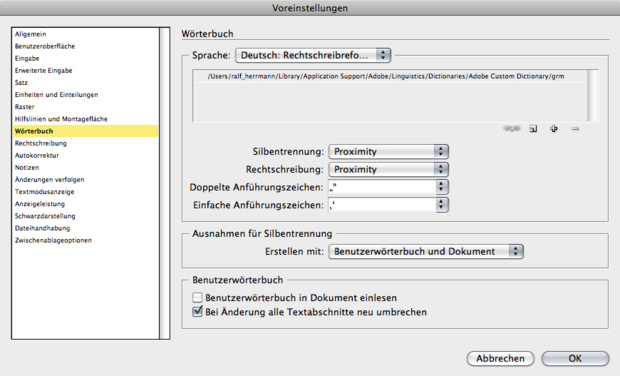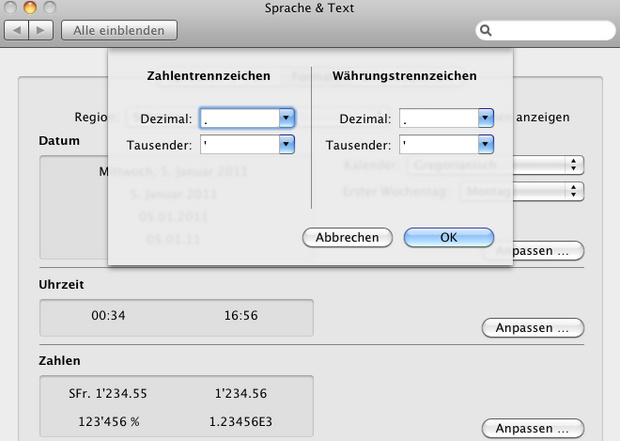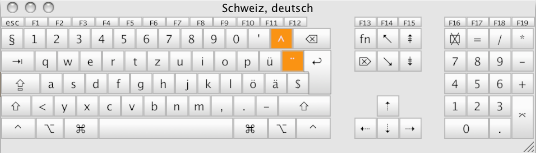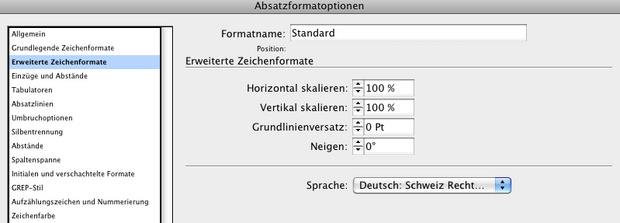
Ich habe ein (hoffentlich) kleines Problem im InDesign CS5 auf Mac OSX. Folgendes Zeichen auf der Schweizer-Tatstatur funktioniert in CS5 (und nur dort) nicht: " ' " anstelle dieses Apostrophes (ist auf der Taste zusammen mit dem " ?" ) kommt immer ein " ‹ ". Mit der Spracheinstellung hat es nicht's zu tun.
Da es in älteren ID-Dokus normal funktioniert, gehe ich davon aus, dass es irgendeine "Einstellung" sein muss, habe aber bis jetzt nicht's gefunden....
Solche automatischen Ersetzungen werden hier im Zusammenhang mit dem Wörterbuch eingestellt:
Der korrekte Apostroph sieht übrigens so aus ’
nicht so: '
An meiner deutschen Tastatur ist die Eingabe   ALT     Umschalt      '
Hallo Ralf
Danke für die rasche Antwort. Du hast ja recht mit dem Apostroph - in der Schweiz (und auf der CH-Tastatur) ist es das sog. "Tausender-Trennzeichen" (ist übrigens in den Systemeinstellungen des Mac OSX auch so)
Bei den "automatischen Ersetzungen" kann man aber nur die Anführungszeichen einstellen, weitere Einstellungen gibt es nicht.
Was mich verwirrt ist wirklich, dass nur dieses (Tausender-Trenn-) Zeichen der "normalen" Tastatur nicht mehr richtig funktioniert... Sobald ich auf die deutsche Tastatur umstelle ist dort (richtigerweise) das "ß".
Und dieser "Fehler" macht es nur im InDesign, in allen anderen Programmen funktioniert es "normal". Auch im ID CS3 macht es diesen "Fehler" nicht!!!!
Gibt es allenfalls bei den Schrifteinstellungen im ID (z.B. Absatzformate) irgend eine versteckte EInstellung?
Bei den "automatischen Ersetzungen" kann man aber nur die Anführungszeichen einstellen, weitere Einstellungen gibt es nicht.
Ja, eben!
InDesign denkt, wenn du dieses Zeichen an ein Wort klebst, dass Du ein schließendes, einfaches Anführungszeichen haben möchtest und ersetzt es dementsprechend. Stell mal auf »Sprache:keine«. Dann dürfte das Problem nicht mehr bestehen.
Du hast ja recht mit dem Apostroph - in der Schweiz (und auf der CH-Tastatur) ist es das sog. "Tausender-Trennzeichen" (ist übrigens in den Systemeinstellungen des Mac OSX auch so)
Ein Apostroph ist auch in der Schweiz ein Apostroph. Selbst wenn du damit die Tausender markierst. Das geradestehende «'» ist das amerikanische Minutenzeichen und heisst – zum Beispiel auch im Pop Char – fälschlicherweise Apostroph. Hier ist das schön beschrieben.
Hoppla - da hab ich mich wohl in die typografischen "Nesseln" gesetzt.....
Also das mit dem "Apostroph" ist schon klar - um das ging es gar nicht (ist auch bei mir Alt+shift+!).
Es ging auch nicht darum, ob das " ' " (amerikanische Minutenzeichen) typografisch richtig ist um als tausendertrennzeichen zu nutzen (1'000)....
Als Gewohnheitstier hat es mich einfach überrascht, dass in IDCS5 dieses Zeichen nicht mehr funktioniert.
Ich habe es auch NICHT an ein Wort geklebt - eben nur als Tausender-Trennzeichen....
@Ralf: Der Tip mit der Spracheinstellung war fast richtig - ich habe es mittlerweile herausgefunden:
In der Absatzformatierung gibt es diese "Sparcheinstellung" unter Erweiterete Zeichenformate" ebenfalls. das "Umstellen" der Sprache dort ist offensichtlich die Lösung... Je nach Spracheinstellung wird dort aus dem " ' " ein "," oder ein " ’ " - Wieso genau - keine Ahnung
Habe ich oben schon erklärt.
Ja schon, aber das ändern der Voreinstellungen hat keinen Einfluss - es ändert erst, wenn man bei den erweiterten Zeichenformaten die Sprache ändert - mir ist deshalb nicht ganz klar, wo diese "Vorgaben" hinterlegt sind....
" ' " anstelle dieses Apostrophes (ist auf der Taste zusammen mit dem " ?" )
Komm mal wieder raus aus den Nesseln. Den Oberlehrer gab ich, weil du in einem Typografie-Fachforum das amerikanische Minutenzeichen Apostroph nennst und mir das eben einfach auffiel. Wenn du in einem Schreiner-Fachforum Arve als Buche verkaufen willst, passiert dir dort dasselbe.
Meinetwegen kannst du eh jedes Zeichen an jede beliebige Stelle setzen. Das machst du ja sowieso, wie du uns anschaulich beweist. Du magst es offensichtlich sehr gerne, findest’s cool als Typ, das Minutenzeichen. ;-)
… nicht's zu tun … nicht's gefunden....
Hat jemand einen Typ?
Schönen Nachmittag weiterhin und «nüt för Uguat, gell!»,
Norbert II
PS: Bei mir auf dem Apfelrechner mit CH-Tastatur und CS5 funktionieren Ralfs Angaben.
Das geradestehende «'» ist das amerikanische Minutenzeichen und heisst – zum Beispiel auch im Pop Char – fälschlicherweise Apostroph.
Auch wenn dieser Strang schon einiges an Staub angesammelt hat...
Hier ein Beispiel, wie stark sich dieses Schreibmaschinen-Ersatz-Zeichen als richtig manifestiert hat, zeicht dieses Video zum Thema:
„In diesem VideoTutorial wird gezeigt, wie Sie in OpenOffice Writer die typographischen Anführungszeichen gegen die “richtigen” ersetzen..“